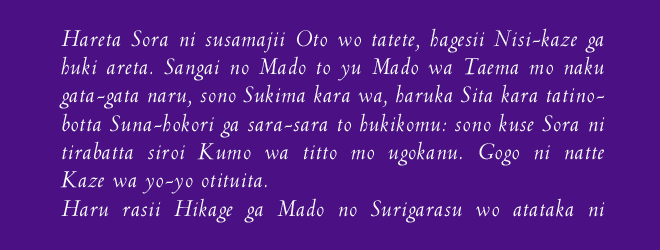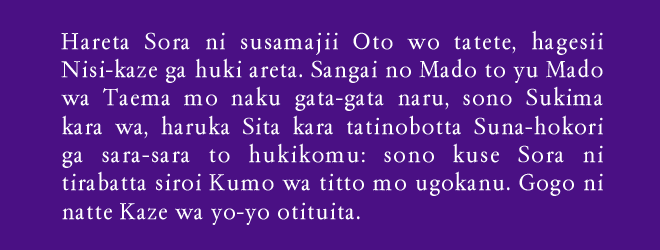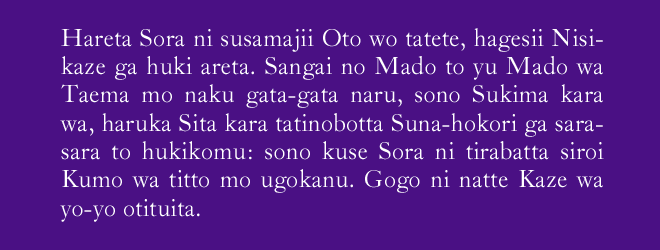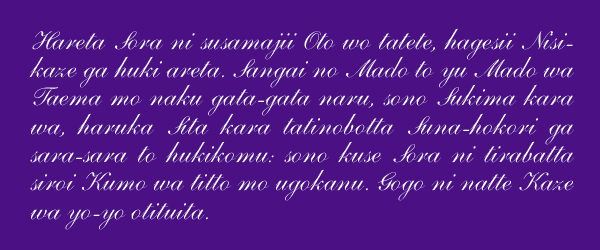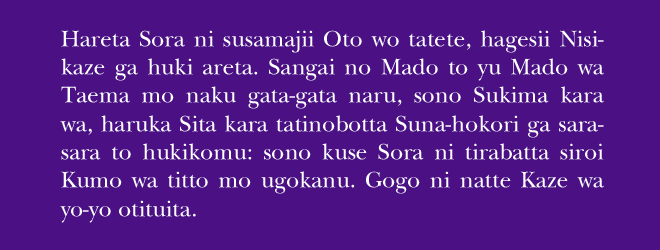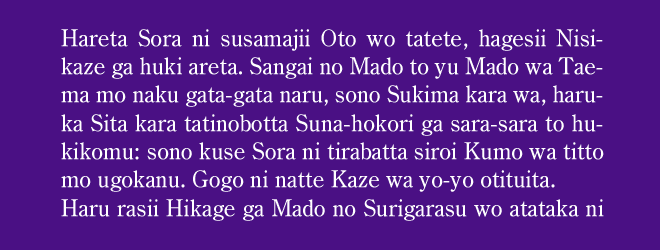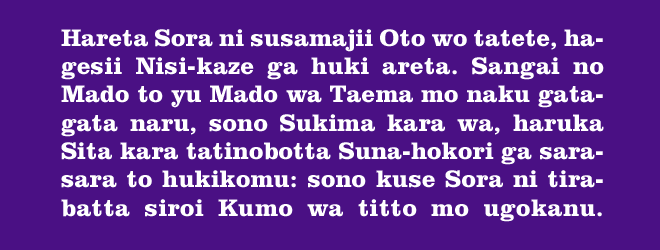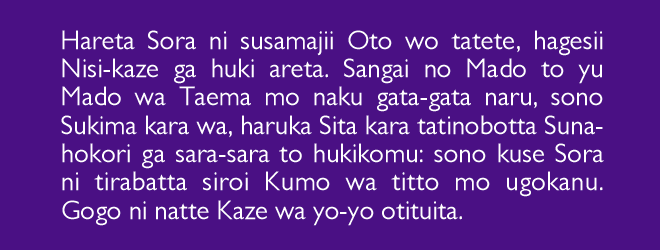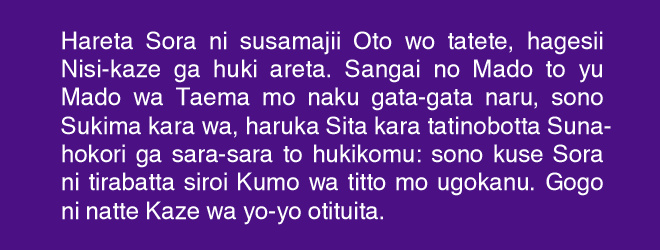
西文字体的历史是欣喜堂《活字字体的基础讲座》中不可分割的一部分,没能赶上前次翻译发表。现在翻译工作终于完成,在此登出,以飨读者。原作者今田欣一先生的一贯主张是,现代日文是一套复杂的书写体系,因此现代日文字体应该分别用和字、汉字、西字三种各自不同的文字体系的字体进行混排。在现代的中日韩字库里,西文字符也是不可缺少的,因此掌握西文字体的基础知识非常重要。
西方印刷术和字体排印学同样有着非常悠久的历史并有其独特的体系,但由于欧洲大陆各国之间的相互影响,整个体系比较繁乱复杂。就目前的中文资源来说,像本文这样以清晰的条理系统地整理各种西文书体的源流的文章,实为少见。尽管今田先生非常谦虚地说西文不是其专行,但对于我们来说,这无疑是一块难得的他山之石。
第一章 大写与小写
Imperial Capital
帝国大写体——罗马帝国的碑文字体
罗马帝国起源于公元前 8 世纪左右拉丁人在意大利半岛的台伯河下游区域建立的古代城市国家。他们于公元前 272 年统一了意大利半岛,赢得了布匿战争[1]的胜利,支配着地中海沿岸一带,但之后内乱不断。最后奥古斯都 (Augustus) 结束内战,并登基为古罗马皇帝,罗马进入了帝国政治时代。
帝国版图在最盛期的五贤帝时代(96—180 年)达到最大,成为一个东至小亚细亚,西到伊比利亚半岛,南抵非洲的地中海沿岸,北达不列颠的强大帝国。五贤帝是指涅尔瓦、图拉真、哈德良、安敦宁·毕尤、马尔库斯·奥列里乌斯这五位皇帝[2],而其中最具代表性的就是图拉真大帝。
图拉真,拉丁语称为「马尔库斯·乌尔皮乌斯·特拉亚努斯」,罗马帝国皇帝,于 98—117 年在位。他协同元老院安定内政的同时,对外征服了亚美尼亚、亚述和美索不达米亚,在位期间使罗马帝国的版图达到了最大。
图拉真大帝的第一项伟绩是征讨达基亚(现罗马尼亚)。为了纪念这场战争胜利罗马人兴建了一座纪念碑,后来成为图拉真墓,位于罗马市区中心的古罗马广场地区。而正是这座 44 米高的大圆柱基座上的碑文,成了「帝国大写体」(imperial capital) 的标志性文字。
而作为「帝国大写体」的手写体,深受抄书员和作家们喜爱的是「俗大写体」 (rustic capital)。这种俗大写体在公元 1 世纪前半到 5 世纪后半叶期间出现的诗人维吉尔(前 70—前 19)的《牧歌集 II》(5 世纪后半)等格调高雅的手抄本中被大量使用。
Carolingian Minuscule
卡洛林小写体——法兰克王国的手写体
法兰克王国是法兰克人在西欧建立的王国。5 世纪末,克洛维统一了法兰克人,于 481 年建立了墨洛温王朝。之后经历数次分裂和统一,由丕平三世于 751 年创建了卡洛林王朝,并在丕平三世之子查理大帝时期迎来了最强盛时期。
查理大帝 (742—814) 是法兰克王国加洛林王朝国王(768—814 在位)。顺便提一下,他的名字用法语称「查理曼」(Charlemagne)、英文称查理大帝 (Charles the Great),德语称「卡尔大帝」(Karl der Große)。他大幅扩张版图,统一了日耳曼各部,由教皇加冕为西罗马皇帝(800—814 年在位),从国王变为了大帝。
查理大帝在统一中央集权整备法制的同时召集了欧洲各地学者振兴学术文艺。这个文化繁荣的时期被史学家称为「卡洛林文艺复兴」。尽管这个时代羊皮纸价格不菲,书籍的需要依然居高不下。查理大帝从约克叫来了高僧阿尔昆[3]并提拔他为图尔的圣马丁大修道院院长。
阿尔昆在修道院里开设了抄写室,将罗马时代后期安色尔体 (uncial) 改为小写的半安色尔体再进行改进,形成了一种新的字体,这就是卡洛林小写体(Carolingian minuscule)。
第二章 Gothic(哥特体)
Textur
从 10 世纪到 11 世纪,安色尔系的卡洛林小写体与俗大写体结合,样式逐渐固定,形成了「俗加洛林体」这一过渡期的字体,已经具有哥特体[4]的显著特征。之后,各地的抄写员又为其加上了各自的区域特征。
在 15 世纪,诞生了笔画末端尖锐的教会专用的正式字体 lettre de forme(正式体) 和带有圆润笔画的非正式字体 lettre de somme(综合体)。另外还有一种法国法令文书专用字体 lettre de batarde(折衷体)。
从教会专用的正式字体 lettre de forme 之后又衍生出了一款叫 Textur 的哥特体。所谓 Textur 意思是平纹编制、线码均匀的布匹。的确,这款字体给人的印象就像织布机里的经线一样整齐。Textur 体据称有德国型、荷兰型和法国型三种,都是字宽狭窄、笔法垂直尖锐的。
最早被制作为印刷用金属活字的是德国型 Textur 体。约翰内斯·古登堡的金属活字就是以当时抄书员书写的 Textur 体为范本制作的,而使用这种活字制作的《四十二行圣经》已经成为古登堡经手制作的印刷品的代名词。
Rotunda
流传到意大利的 lettre de somme 系字体是 Rotunda 体,它把 Textur 简化后将笔画变圆,被称为 Textur 和后述的 Schwabacher 之间的一种过渡期字体。它又被称为圆哥特体,盛行于意大利。升部和降部都很短,字宽稍微宽一些。
金属活字的 Rotunda 刊载于威尼斯的埃哈德·拉特多尔特 (Erhard Ratdolt,1447—1528) 发行的活字字体样本册(1486 年)。它很适合拉丁文,因此纽伦堡的安东·科贝格 (Anton Koberger) 于 1493 年将其用在了《纽伦堡编年史》拉丁文版中。
Rotunda 铅字的影响从意大利扩大到了法国、西班牙,一直被使用到 17 世纪。但在北部欧洲几乎都没有用它,大概是因为北部欧洲不是拉丁语区,所以它没有成为一款普遍使用的字体。
Fraktur
以 lettre de batarde 为原型诞生的有 Schwabacher 和 Fraktur 体。与所有笔画垂直的 Textur 体不同的是,Schwabacher 的文字两端圆滑,升部上端有尖划。而 Fraktur 的特征是一侧圆一侧垂直。
Schwabacher 体的金属活字是在 1470 年以后出现的。把 Schwabacher 作为正文字体使用的书籍有美因茨的彼得·舍费尔 (Peter Schöffer,?—1520) 的印刷品、《纽伦堡编年史》的德语版(1493)等。1490 年至 1540 年间 Schwabacher 金属活字是德国最受欢迎的字体。
到了 16 世纪前半叶,印刷商约翰·诺伊德费尔(Johann Neudörffer,1497—1563)与字冲雕刻师希罗尼穆斯·安德烈埃 (Hieronymus Andreä) 一起从 Schwabacher 铅字里派生出了金属活字的 Fraktur。之后,Fraktur 铅字成为最具代表性的德国哥特体,而 Schwabacher 字体退为辅助性使用。画家阿尔布雷希特·丢勒 (Albrecht Dürer) 的理论著作中也使用了 Fraktur 铅字。
第三章 Venetian(威尼斯式罗马正体)
Humanist
人文主义体
人文主义 (humanism) 是指,在通过研究希腊、罗马的经典著作掌握普遍性修养的同时,把人类从中世纪以基督教为中心的社会中解放出来,以复兴人性为目标的精神运动。这种风潮在文艺复兴时期随着意大利的商业城市的繁荣,逐渐波及到欧洲各地。而推动这一风潮的就是人文主义者们。
人文主义者们认为,以往使用的哥特体野蛮而低级趣味,应该抛弃。他们主张在介绍希腊和罗马经典的时候不应该用哥特体,因为那会使人意识到中世纪基督教的权威。
15 世纪初人文主义者使用的字体是从卡洛林小写体改进而成的人文主义小写体 (humanist minuscule) 和继承了罗马时代俗大写体风格的人文主义大写体 (humanist capital)。这些书体作为文艺复兴时期的代表性字体风靡一时。
Sweynheim and Pannartz
斯韦恩海姆与潘纳尔茨
将印刷术从德国介绍到文艺复兴时期的意大利的是康拉德·斯韦恩海姆 (Konrad Sweynheim,?—1477) 和阿诺尔德·潘纳尔茨 (Arnold Pannartz,?—1476)。两人都曾是在德国美因茨的谷登堡印刷厂里工作的印刷工人。
1464 年他们在罗马郊外的苏比亚科 (Subiaco) 修道院里建立了意大利第一家印刷厂。在那里,他们为了迎合意大利的读者,以人文主义者们所使用的手写字体为范本制造了活字。
这种活字受到了人文主义印刷者们的欢迎。因为它是从哥特体向威尼斯式罗马体转移过程中的一个过渡产物,故被称为「前罗马体」(pre-roman)。
Speyer Brothers
斯皮拉[5]兄弟
在人文主义者云集、印刷需求不断增长的威尼斯最早建造印刷厂的,是来自德国的斯皮拉兄弟:约翰·施派尔 (Johann Speyer,?—1470) 和文德林·施派尔 (Wendelin Speyer,?—1478)。斯皮拉兄弟意识性地往小写字母里加入衬线,目的是能与大写字母更搭配。这样就比单纯模仿手写文字的「前罗马体」更进了一步,形成了样式化的威尼斯式罗马正体。
Nicolas Jenson
尼古拉·让松
将威尼斯罗马体集大成的是法国印刷商尼古拉·让松 (Nicolas Jenson,1420?—1481)。让松设计的字体比斯皮拉兄弟的活字更洗练洒脱,并易于阅读,当今罗马正体的始祖——威尼斯式罗马正体终于走向了成熟。
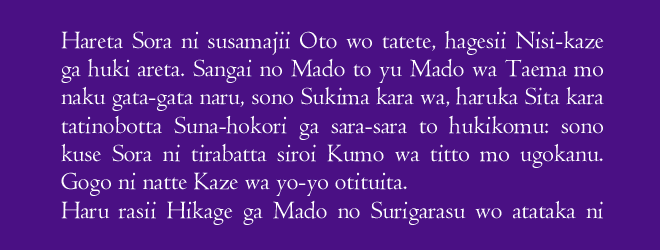
让松于 1458 年被派往美因茨的古登堡处。虽然不知道他在印刷厂里干了多长时间,但据推测他在 1468 年到了威尼斯,为古登堡印刷厂里共事的斯皮拉兄弟制作活字。约翰·施派尔过世后,让松得到了商人们的资金援助,自己开设了印刷厂,使用高度成熟的活字开始了印刷活动。
使用让松活字的有普林尼[6]所著《博物志》(1472)。该书是公元 1 世纪的论述家普林尼唯一现存的著作,是一部网罗古典罗马世界知识的百科全书。而使用让松活字印刷的《博物志》被认为是活字版印刷史上最重要的印刷品之一。
Albert Bruce Rogers
阿尔伯特·布鲁斯·罗杰斯
世人重新开始关注尼古拉·让松的活字是近代以后的事情。以「艺术与工艺运动」而闻名的威廉·莫里斯 (William Morris,1834—1896) 为追求理想的书籍在 1890 年设立了科尔姆斯科特出版社 (Kelmscott Press),模仿让松的活字制作发布了 Golden Type(黄金字体)。
深受莫里斯影响的美国书籍装帧师阿尔伯特·布鲁斯·罗杰斯 (Albert Bruce Rogers,1870—1957) 把让松的活字字体复刻成了 Centaur 体。
恩斯赫德活字铸造所 (The Enschedé Font Foundry),1991 年成立于荷兰哈勒姆。
欧塞尔 (Auxerre) 位于法国中部,在勃艮第大区、巴黎与第戎之间,是约讷省的首府。
《字体排印手册》,原书名为 Manuel typographique utile aux gens de lettres et à ceux qui exercent les différentes parties de l’art de l’imprimerie,与约瑟夫·热拉尔·巴布(Joseph Gérard Barbou)合著。
贝特霍尔德活字铸造所 (Berthold Type Foundry) 1858 年由赫尔曼·贝特霍尔德 (Hermann Berthold,1831—1904) 在柏林创办,主要出品了 Akzidenz-Grotesk 等字体。
深受美国影响的韩国日本,至今仍将「黑体」称为「哥特体」,作者在此是想澄清事实。参照注解 4。
Walbaum 字体家族,由尤斯图斯·埃里希·瓦尔鲍姆 (Justus Erich Walbaum,1768—1839) 于 1800 年左右设计。